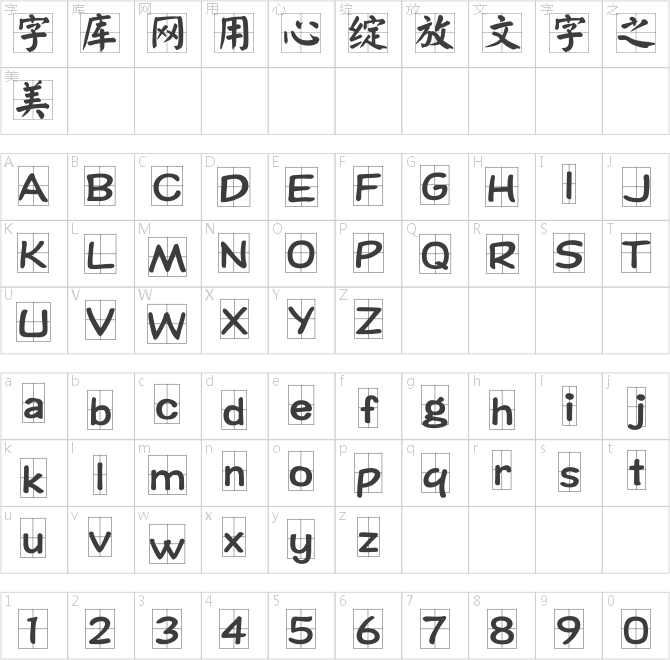
字体名称: 文鼎习字体简繁
文鼎习字体简繁
本人将「文鼎大颜楷big5」合并入「文鼎习字体」并将所添加的汉字加了「文鼎习字体」的田字格形成了「文鼎习字体简繁」。原生兼容新版win10。
文鼎习字体简繁字体字库是一款让人赏心悦目、百看不厌的中文字体,适合各类广告和产品包装设计应用,字体大小17.94MB,格式为ttf字体,上传用户是伊宁,作者/版权方为文鼎字库